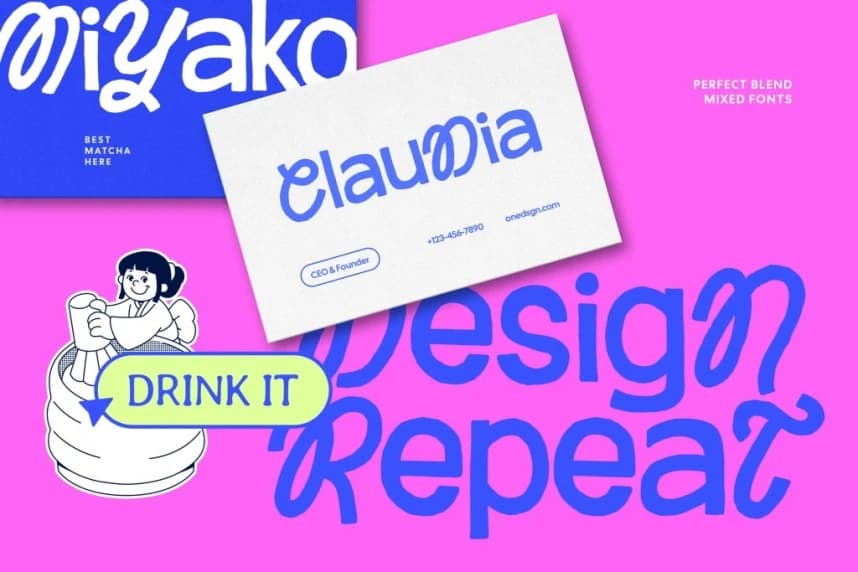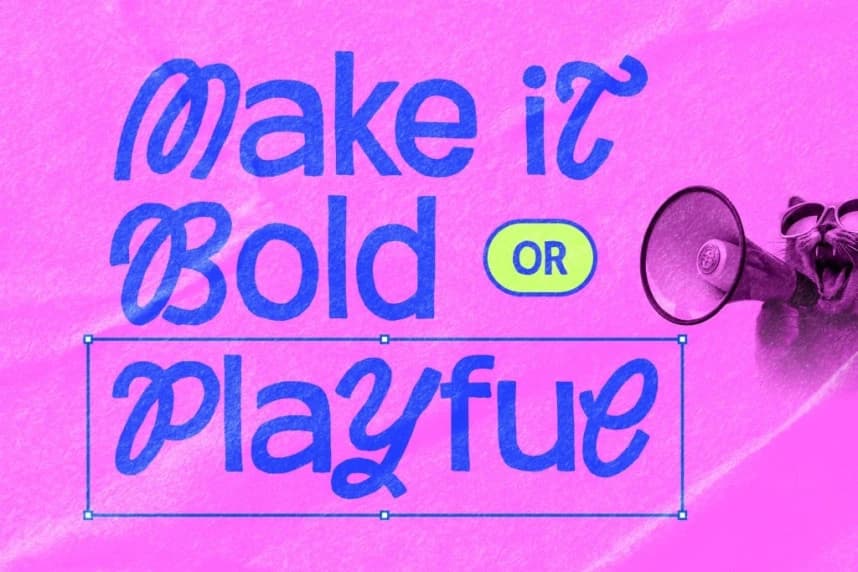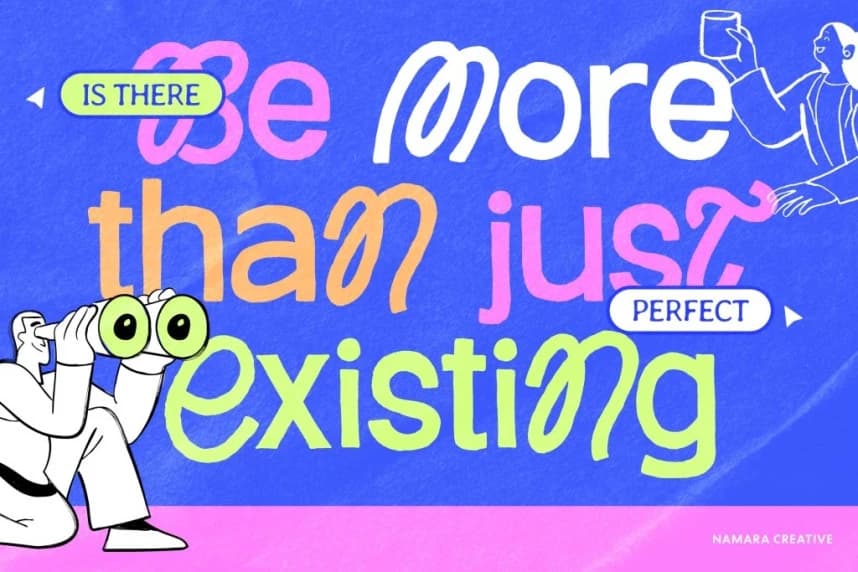
Rolly Pulfy Font
Rolly Pulfy Font – Playful hibrit sans yazı tipi, tasarımlarınıza neşe, kişilik ve modern çekicilik katmak üzere tasarlandı. Temiz sans-serif yapıyı el çizimi, yuvarlak hatlı harflerle birleştirerek, Rolly Pulfy cesur netlik ile samimi ifade arasında mükemmel bir denge kuruyor.
Rolly Pulfy Font- Neşeli hibrit sans yazı tipi, tasarımlarınıza neşe, kişilik ve modern çekicilik katmak için tasarlandı. Temiz sans-serif yapıyı el çizimi, yuvarlak hatlı harflerle birleştirerek, Rolly Pulfy cesur netlik ile arkadaşça ifade arasında mükemmel bir denge kurar.
Rolly Pulfy